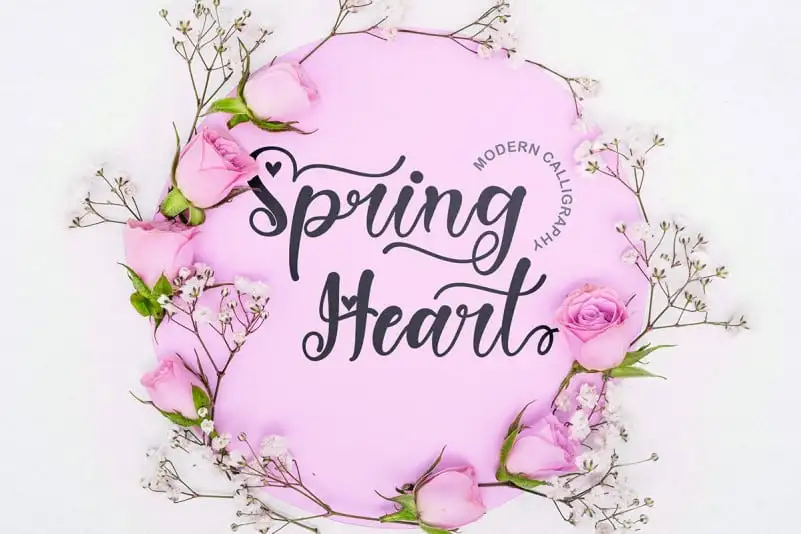
Spring Heart Calligraphy Font – Download Grátis
Esta fonte se chama “Spring Heart Calligraphy Font”, uma combinação perfeita de primavera e um coração acolhedor. Essa é uma fonte calligrafia que impressiona por sua beleza única, facilidade de uso e adorável personalização em cada letra. As adiçãozinhos nos caracteres são simplesmente fáceis de usar, sem esquecer das instruções para manipulá-las a seu gosto. É perfeita para uma variedade de projetos que envolvem o entardecer da primavera, casamentos, Dia das Mães e dos Pais, Dia do Pai, Páscoa, Dia da Terra ou qualquer outra ideia criativa que lhe venha à mente.